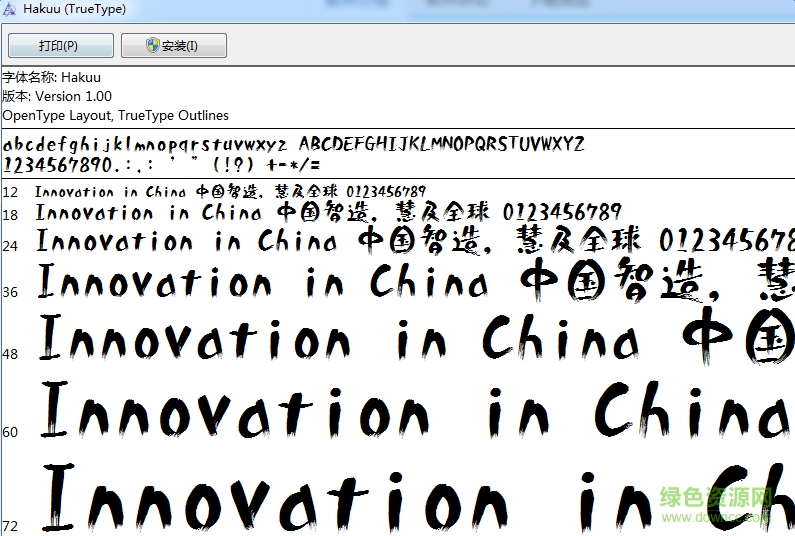
hakuu英文字體
hakuu字體是一款超好用的個(gè)性英文字體,該字體可以廣泛應(yīng)用于美術(shù)設(shè)計(jì)、新聞媒體、宣傳海報(bào)、ppt、影視制作以及任何使用文字的領(lǐng)域,有需要的朋友可以免費(fèi)下載收藏。
hakuu字體擁有超飄逸的筆風(fēng),墨彩飛動(dòng),讓用戶感受到一種極致的美感。有喜歡的朋友趕快來綠色資源網(wǎng)下載使用吧!